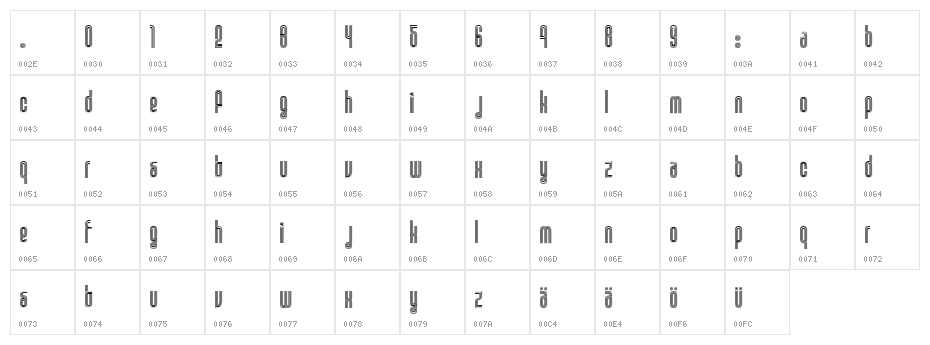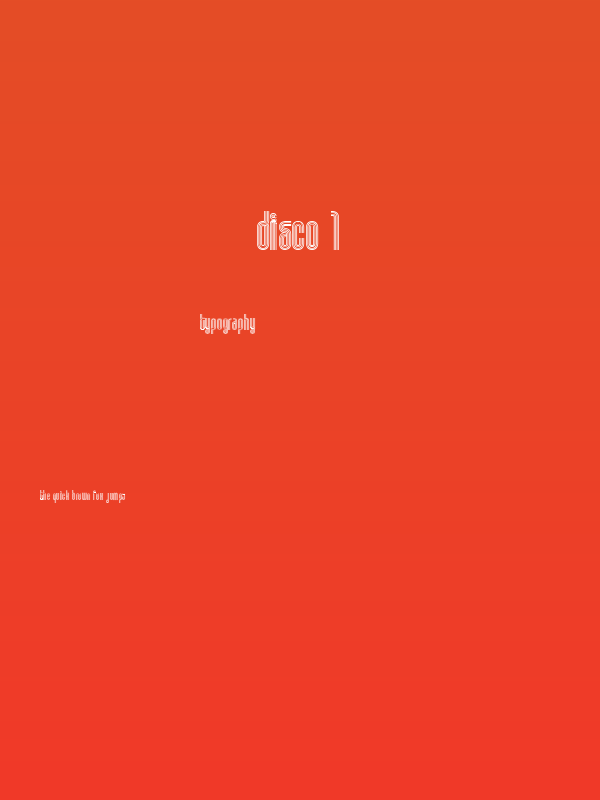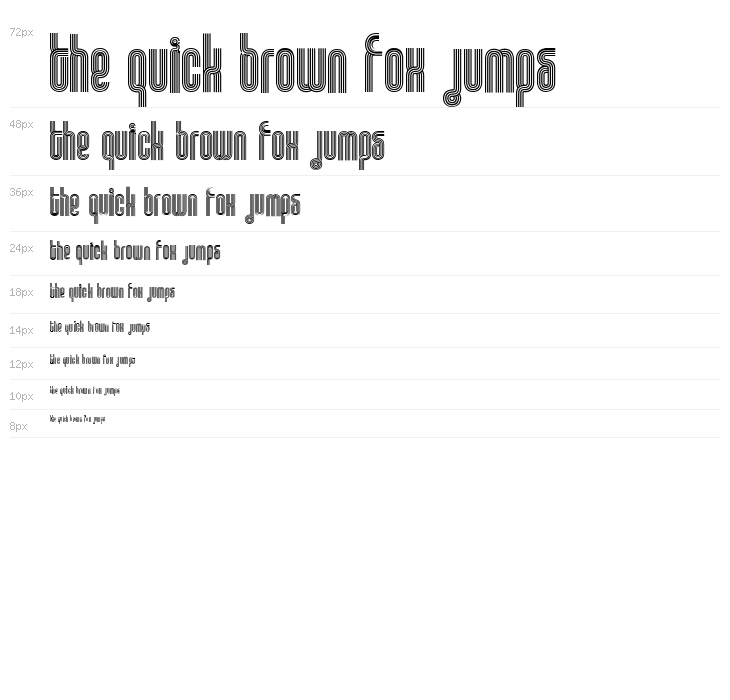
Disco 1 Font
| Progetti proposti | Ideal for retro-themed posters, album covers, event flyers, and branding projects that require a bold, eye-catching typeface. |